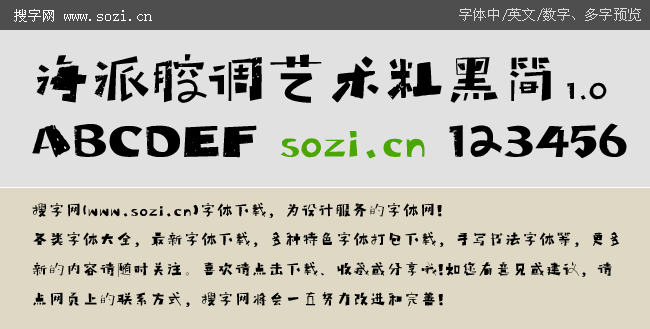
海派腔調(diào)藝術(shù)粗黑簡1.0
搜字網(wǎng)提供一款海派腔調(diào)藝術(shù)粗黑簡1.0中文字體下載,海派腔調(diào)藝術(shù)粗黑簡字體是一款左粗右細(xì)、整體效果非常出眾的簡體中文字體,適合應(yīng)用于廣告設(shè)計、名片設(shè)計、包裝印刷、產(chǎn)品設(shè)計等應(yīng)用。